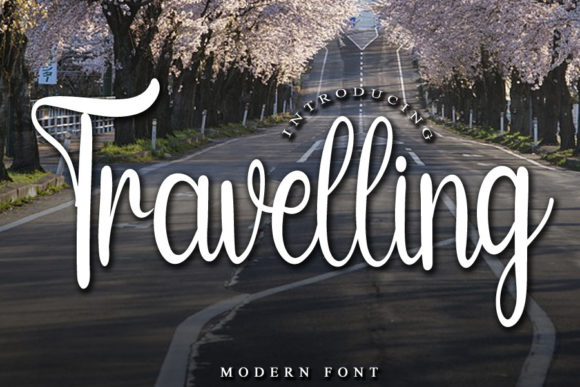
Travelling
Пошук відповідних елементів дизайну може бути складним, але Travelling пропонує виняткову колекцію, яка миттєво покращить вашу роботу.
Незалежно від того, чи створюєте ви продукти POD (друк на вимогу), весільні запрошення або графіку для соціальних мереж, Travelling стане ідеальним вибором.